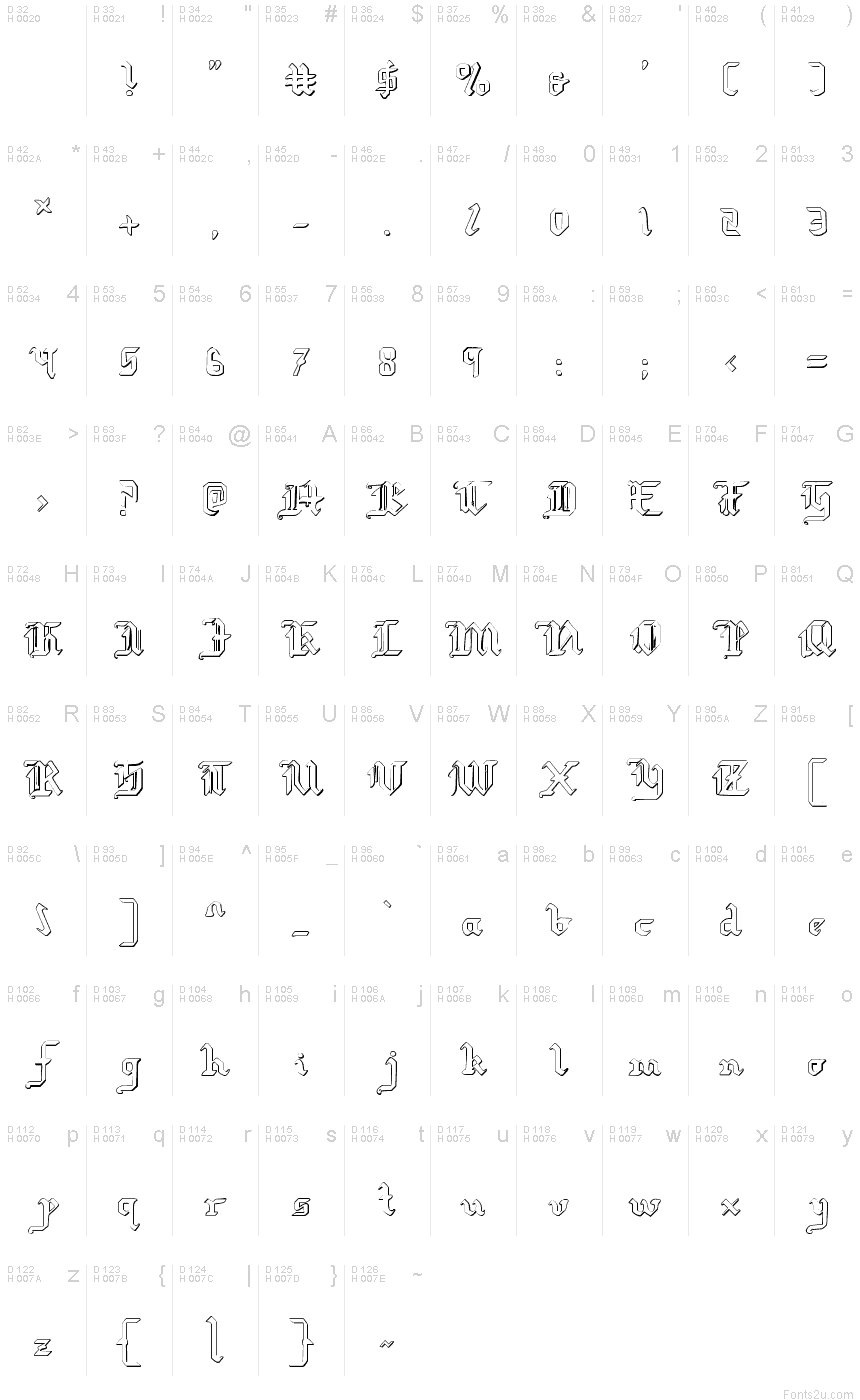
Redcoat Shadow von Iconian Fonts ist eine kostenlose, konturierte Blackletter-Display-Schrift mit einer theatralischen, mittelalterlichen Note. Eckige Striche, geschwungene Verzierungen und versetzte Innenschatten verleihen den Buchstaben die geschnitzte Tiefe eines alten Wirtshausschildes oder eines illustrierten Buchtitels.
Dieser mehrschichtige Schatten sorgt für sofortige Dramatik auf Fantasy-Plakaten und Game-Titelbildschirmen, während die spitzen Formen Albencovern und Themenverpackungen einen historischen Look verleihen. Verwenden Sie diese kostenlose Schrift für Event-Flyer oder wirtshausinspiriertes Lettering, wenn das Design nach einer Schrifterscheinung verlangt, die heraldisch, verspielt und leicht ungezügelt wirkt.